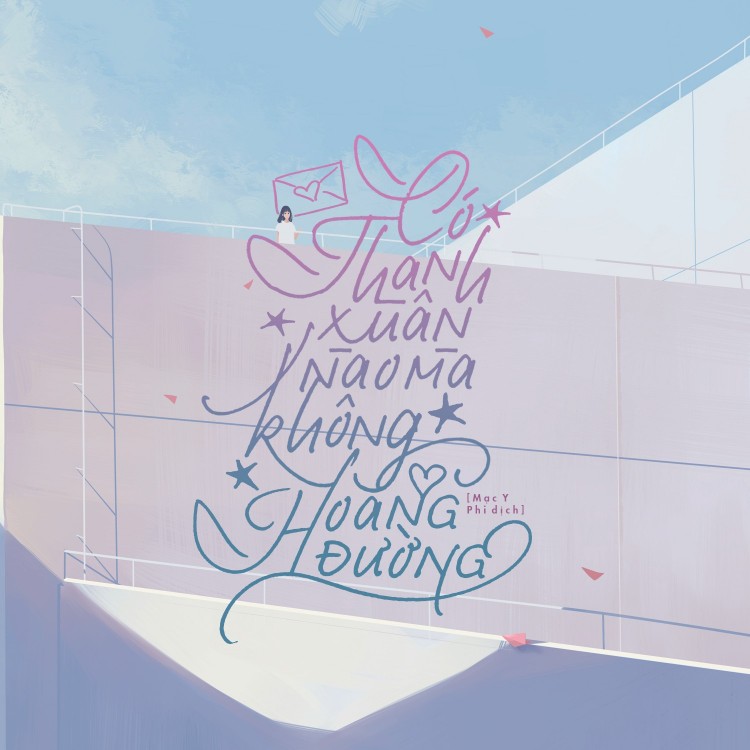
Font việt hóa MTD Casanova Script EF Pro
Trong thế giới đồ họa hiện đại, việc lựa chọn một bộ Font Miễn Phí chất lượng đóng vai trò quyết định đến sự thành công của tác phẩm. Font việt hóa MTD Casanova Script EF Pro nổi lên như một lựa chọn hàng đầu nhờ sự kết hợp hoàn hảo giữa nét vẽ thanh mảnh và phong cách nghệ thuật cổ điển. Đây là bộ phông chữ thuộc dòng Script, mang lại cảm giác mềm mại, uyển chuyển, giúp các bạn học sinh và giáo viên dễ dàng tạo ra những tài liệu học tập hoặc thiệp mời mang tính thẩm mỹ cao.
Đặc điểm nổi bật của Font việt hóa MTD Casanova Script EF Pro
Sự tinh tế trong từng đường nét
Bộ Font việt hóa MTD Casanova Script EF Pro sở hữu những đường cong uốn lượn đầy nghệ thuật. Mỗi chữ cái đều được chăm chút kỹ lưỡng, đảm bảo tính liên kết tự nhiên khi ghép chữ. Đặc biệt, phiên bản việt hóa này đã được tối ưu hóa hoàn toàn để không xảy ra lỗi hiển thị các dấu tiếng Việt phức tạp như dấu hỏi hay dấu ngã.
Tính ứng dụng linh hoạt trong đời sống
Nhờ vẻ ngoài sang trọng, phông chữ này thường được ứng dụng trong các thiết kế bìa sách, nhãn vở, và đặc biệt là các chứng chỉ khen thưởng tại trường học. Ngoài ra, các em học sinh có thể sử dụng nó để làm nổi bật tiêu đề trong các bài thuyết trình PowerPoint, tạo ấn tượng mạnh mẽ với thầy cô và bạn bè thông qua sự chỉn chu và sáng tạo.
Lưu ý khi sử dụng và kết luận